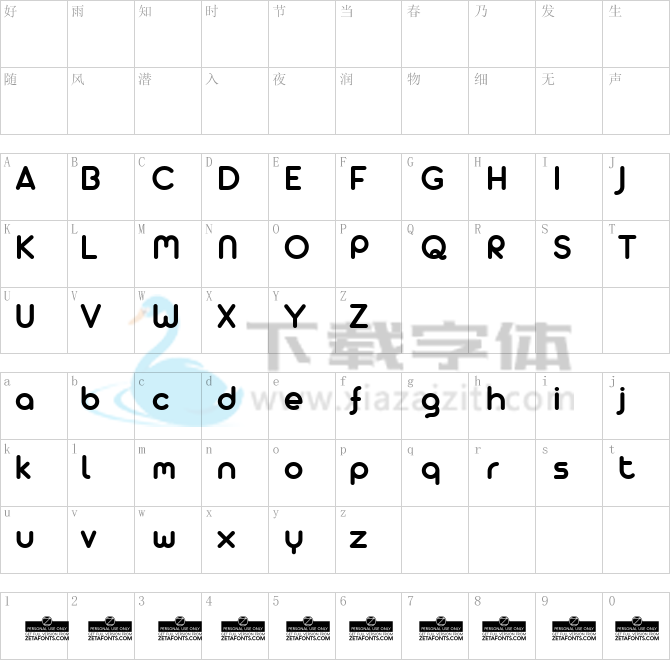
Arista Pro Alternate SemBd.ttf字体下载
Arista Pro Alternate SemBd.ttf字体下载,这款字体结构工整、笔画清晰,兼顾美观与易读性,适用于标题、正文、海报、包装、LOGO 等多种场景。字形优雅稳定,风格百搭耐看,适配日常排版与创意设计,让文字呈现更舒适、更具质感。Arista Pro Alternate SemBd.ttf字体下载一笔一画,皆是细节,以均衡的比例、流畅的线条打造舒适视觉体验,字形端正大气,风格简约现代。无论是商业设计、品牌宣传还是日常排版,都能轻松驾驭,让文字更有格调与力量。Arista Pro Alternate SemBd.ttf字体下载字体下载。